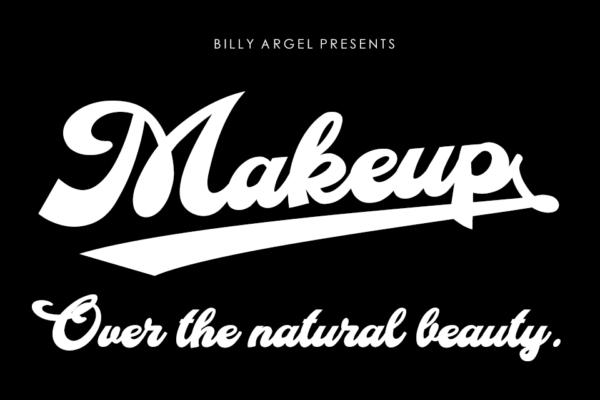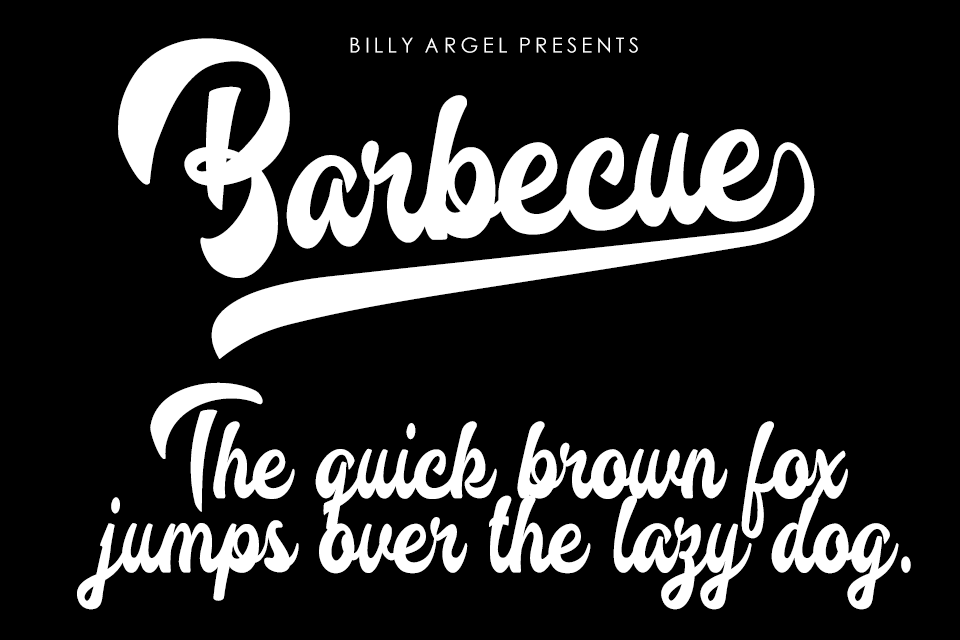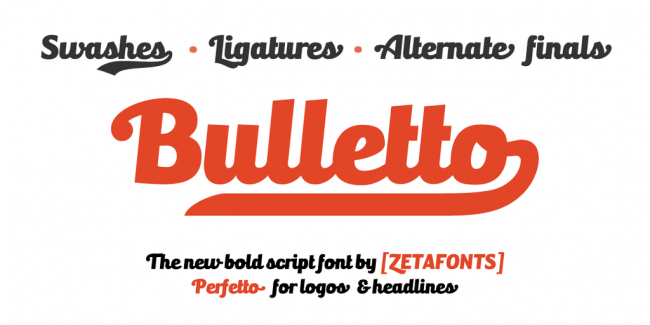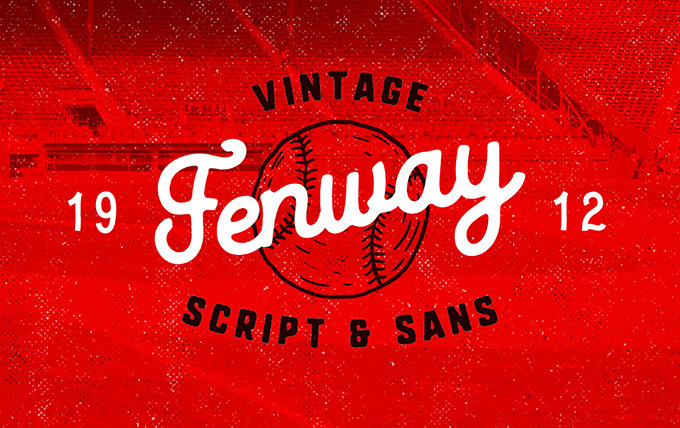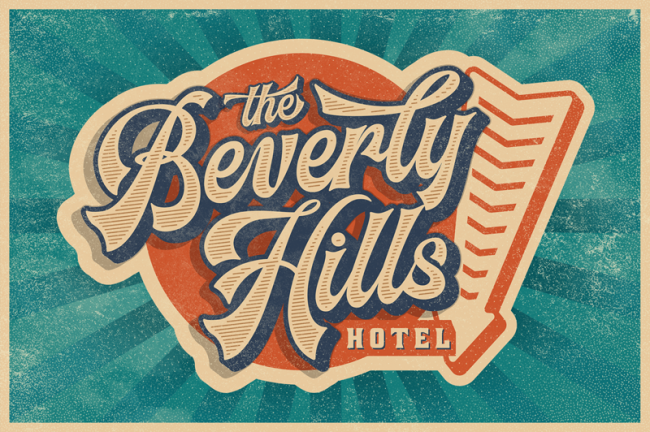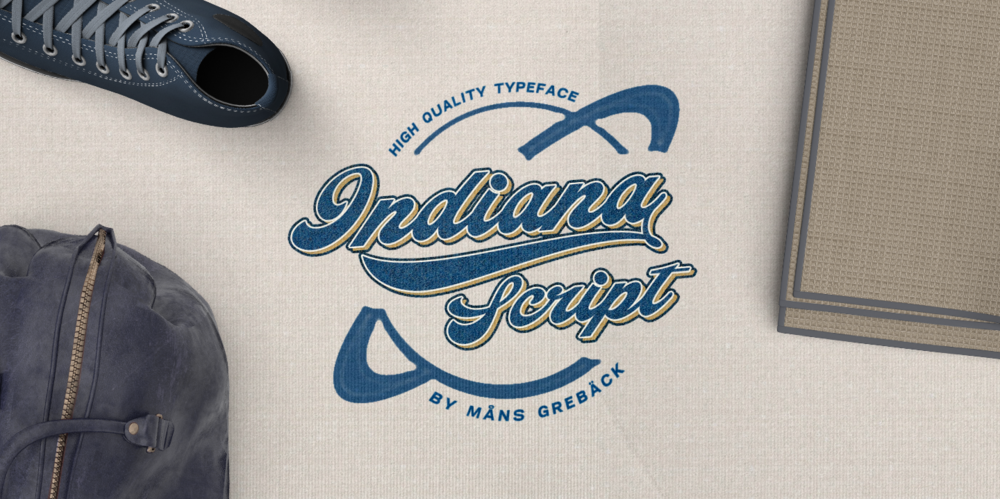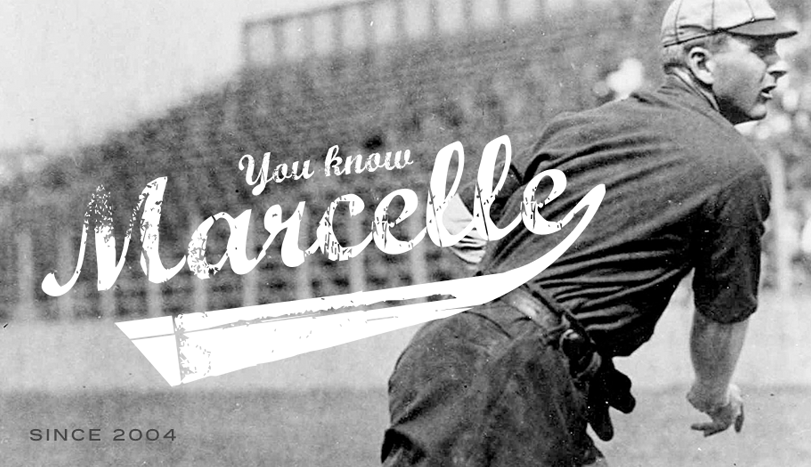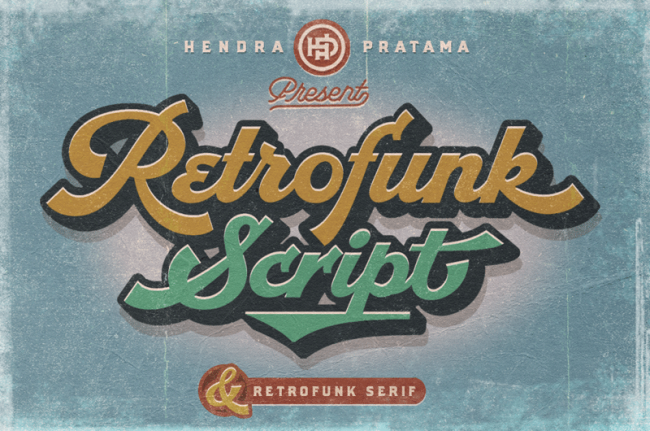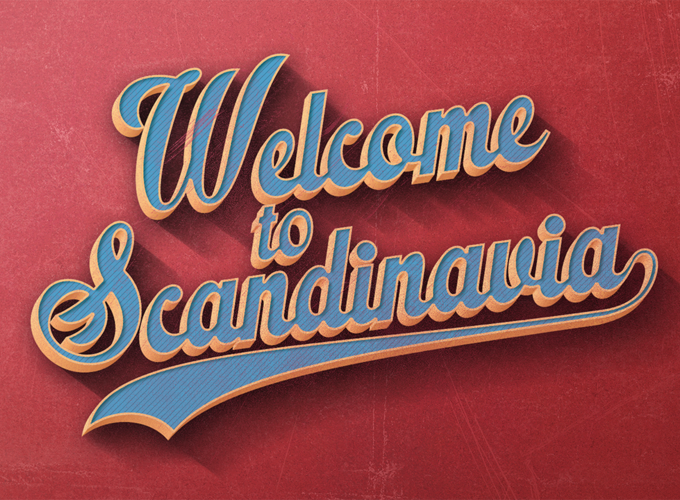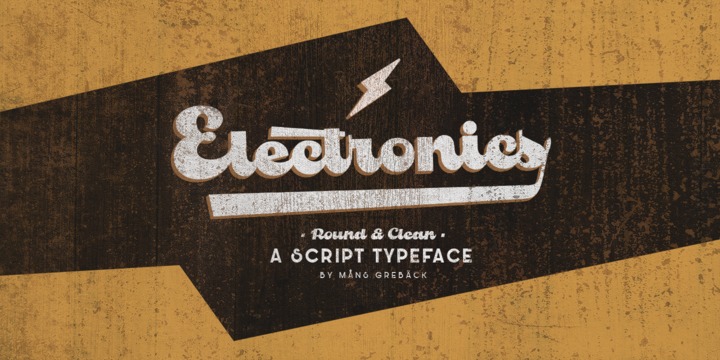
14 typographies sur le sport à télécharger gratuitement
Le sport et ses différentes disciplines ont toujours été une inspiration pour les créatifs…
Vous possédez une marque de sport ou une team sportive, qui nécessite une nouvelle identité visuelle ? Pourquoi ne pas donner un coté vintage à votre logo pour vous démarquer ?
Voici une sélection de typographies gratuites qui vous sera très utile dans l’élaboration de logo, posters, flyers dans le secteur du sport ou du e-sport.